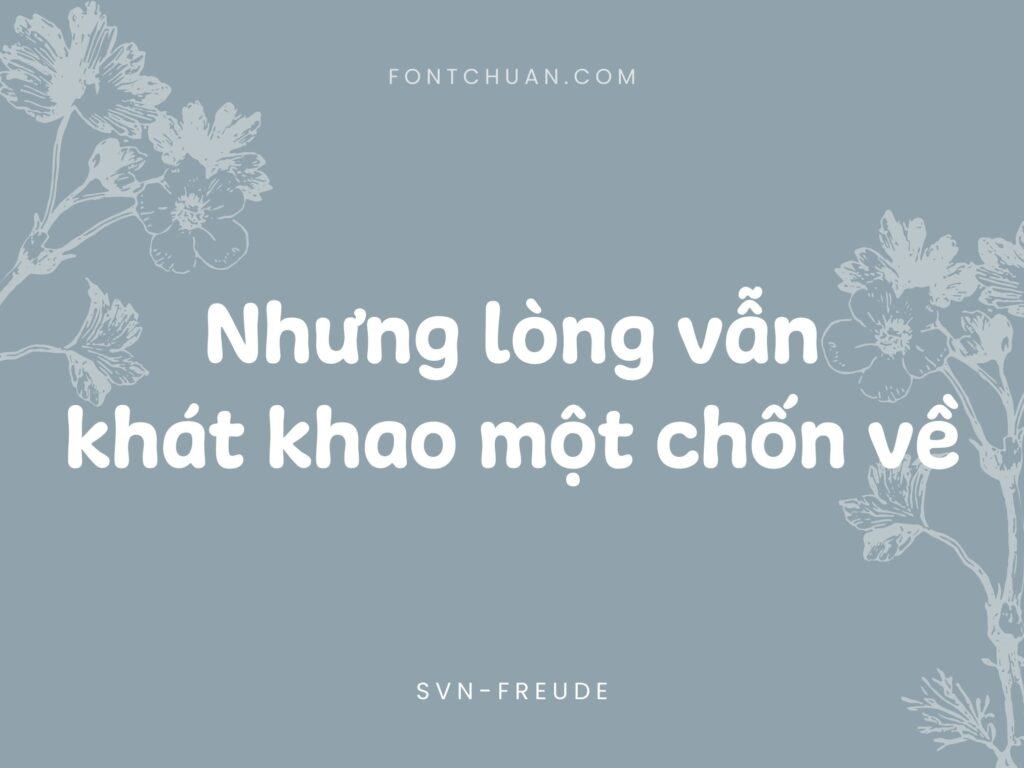
Font SVN Freude Việt Hóa
Tác giả Font: Thomas Gabriel
Font SVN Freude là phiên bản Việt hóa của kiểu chữ Freude, được thực hiện bởi Styleno.1 Fonts. Freude là một kiểu chữ sans-serif hiện đại, nổi bật với các đường nét mềm mại và tinh tế, tạo cảm giác thân thiện và dễ đọc. Font này thích hợp cho nhiều mục đích sử dụng khác nhau, từ thiết kế logo, tiêu đề đến các ấn phẩm truyền thông.
SVN Freude lý tưởng cho các dự án thiết kế yêu cầu sự hiện đại và chuyên nghiệp, như thiết kế logo, tiêu đề, bao bì sản phẩm và các ấn phẩm quảng cáo. Các ngành nghề như quảng cáo, giáo dục và công nghệ có thể tận dụng font này để tạo điểm nhấn trong thiết kế. Ngoài ra, font cũng thích hợp cho các sự kiện như Tết, Giáng sinh, Valentine và các lễ hội khác.